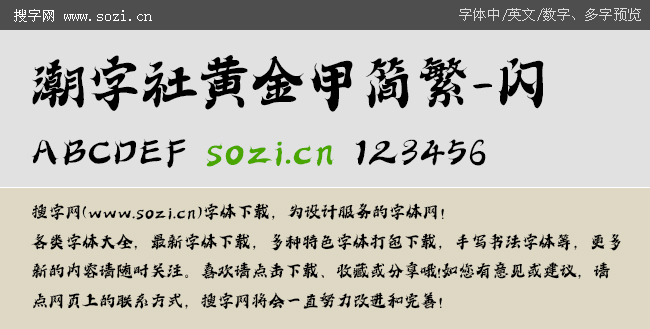
潮字社黃金甲簡繁-閃
搜字網提供一款潮字社黃金甲簡繁-閃中文字體下載,潮字社黃金甲簡繁-閃是一款非常獨特的個性毛筆藝術字體,這款字體總體結構較為方正,在楷書的基礎上稍加隸書的圓潤、舒展之氣。筆畫入勢鋒芒盡顯,增加了字體的靈動性。字形撇捺開張,線條對比強烈,時而纖巧,時而厚重,波折起伏,巧于變化。運筆俯仰呼應,各有所據。字體擒縱自如,深具唐楷之意和古隸之美。適合應用于藝術設計、平面宣傳設計、網頁設計等領域等應用。(本字體為個人非商用版,商用請聯系作者購買授權。官方網址:http://www.reeji.com 聯系方式:021-58597892)